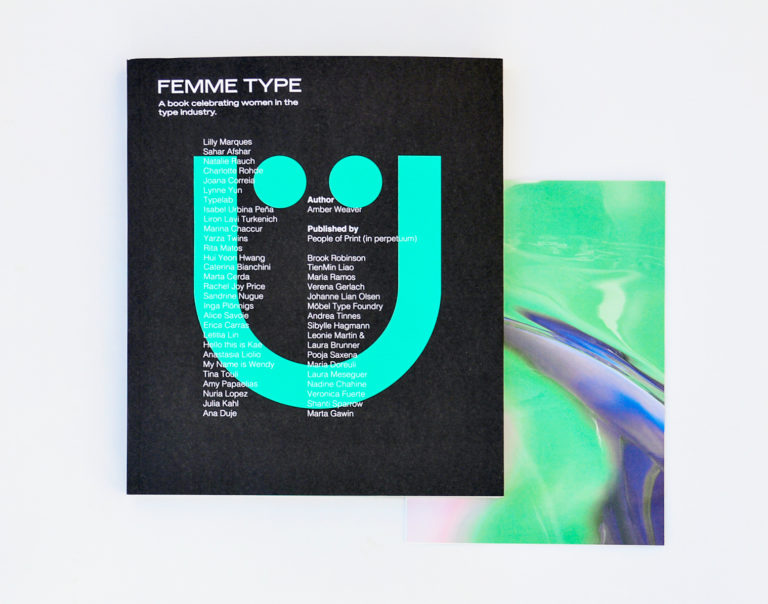
Mujeres en tipografía: Femme Type
«Estadísticamente hay más nombres de hombres que de mujeres en los libros de diseño. Tiene que haber más mujeres en el campo de la tipografía y la impresión que estén produciendo trabajos inspiradores, ¿por qué no son incluidas en estos libros y sus trabajos no aparecen en las plataformas online de inspiración?» Esta breve reflexión fue la que llevó a Amber Weaver a concebir Femme Type, una publicación exclusivamente femenina que «celebra» las obras de 40 mujeres de talento más que contrastado en la industria tipográfica con el objetivo de crear una obra que inspire a otras mujeres (y hombres) a seguir una carrera profesional en el campo de la Tipografía.
El concepto
Encontrar a estas mujeres y ensalzar sus trabajos en una publicación se convirtió en una misión para Weaver, lo que la llevó a crear una plataforma en Instagram con el fin de crear una comunidad y una red creativa donde compartir su pasión por las letras, además de llevar a cabo una campaña de Kickstarter, que en tan solo tres días consiguió la meta de financiación con un increíble apoyo por parte de multitud de patrocinadores anónimos. La respuesta de colaboración por parte de diseñadoras fue, también, más que positiva, ayudando a crear la simbólica y significativa obra que es Femme Type.
El libro
Femme Type se divide en tres secciones: ensayos, diseño tipográfico y tipografía.
Abre el libro el ensayo de la diseñadora de tipografía española María Ramos,sobre tipografía para máquinas de escribir y su influencia en las fuentes digitales, un profundo ejercicio de análisis sobre las tipografías monoespaciadas, en el que repasa las formas de los caracteres diseñados con unos propósitos concretos, el método de impresión y los factores que implican la apariencia final en papel, las novedades que trajeron los modelos de máquinas de escribir electrónicos y cómo, a pesar de que typewriter no es un estilo tipográfico concreto, se han diseñado tipografías que recrean la apariencia de textos escritos con estas máquinas. Como colofón, Ramos se detiene a analizar algunas de las más relevantes tipografías enmarcadas en esta tendencia desde el comienzo de la «era digital tipográfica» hasta nuestros días.
El segundo ensayo pertenece a TienMin Liao, diseñadora y tipógrafa neoyorquina especializada en lettering personalizado, tipografías para marcas y realización de logotipos kanji/chino. En su ensayo nos habla de la rotulación (o lettering) bilingüe, documentando alrededor de cincuenta ejercicios de combinación de sistemas de escritura latino y kanji, uno de los tres sistemas de escritura japonesa. En su texto, Liao examina las diferencias en el contorno, densidad y forma entre el latín y el kanji, hallando diferencias estructurales que suponen el principal reto a la hora de enfrentarse al desarrollo de un proyecto tipográfico bilingüe. Un extenso ensayo, lleno de detalles, que revela no solo una serie de enfoques para resolver el diseño bilingüe sino la riqueza de los sistemas de escrituras. No solo de latín vive la tipografía.
El apartado de diseño tipográfico muestra el espléndido trabajo de veintiocho talentosas diseñadoras de tipografía con breves reseñas biográficas y descripciones de los correspondientes proyectos, además de sus respectivas webs o contactos en las redes. Entre este elenco de altura, subrayamos, por el simple hecho de resultar de un modo u otro cercanas a quien suscribe, la presencia de Nuria López, Laura Meseguer, Joana Correia, Alice Savoie, Sandrine Nugue, Inma Plönnings, Nadine Chadine o Verena Gerlach. De todos modos, podemos decir que las veintiocho compañeras presentes en esta sección, algunas desconocidas hasta ahora, forman ya parte de nuestro acervo tipográfico.
Dentro de esta mismo sección figuran también tres artículos especiales firmados Typelab, Alphabettes y Slanted.
Este apartado muestra una calidad excepcional en conceptos, en ejecución, dibujo y usos, iluminando un carrusel de artes finales inspiradores y tremendamente comunicativos. Sistemas modulares, estructuras, deconstrucción, reinterpretaciones, diseños tipográficos inclusivos, experimentación, diferentes sistemas de escritura… un rico y pujante panorama creativo que ensancha los límites del diseño tipográfico.
El último apartado, llamado «Tipografía», incluye una entrevista con la fundadora de Hey Studio en Barcelona, Veronica Fuerte, y muestra los espectaculares trabajos de lettering y tipografía creativa de diseñadoras como Shanti Sparrow, Rita Matos, el estudio londinense Yarza Twins, My Name is Wendy o la barcelonesa Marta Cerdá. Una vez más descubrimos nombres que no teníamos en nuestro radar y volvemos a sentirnos abrumadas (y felices) por tanto talento y profesionalidad.
La guinda del pastel la pone Production Type con un espécimen de regalo incluido en la publicación.
Femme Type otorga visibilidad al trabajo de las diseñadoras, muestra un enriquecedor escenario en el campo tipográfico y es, sin duda, una obra inspiradora para diseñadoras y diseñadores del presente así como una herramienta educativa para las siguientes generaciones.
Ficha técnica
• Título: Femme type | A book celebrating women in the type industry
• Autora y diseñadora: Amber Weaver
• Editorial: People of print
• Género: tipografía
• Idioma: inglés
• Encuadernación: tapa blanda
• Tintas: cmyk + Pantone 3245U
• Papel: Fedrigoni Arcoprint. Cubierta 300 g, interior 100 g
• Medidas: 250 x 210mm
• Páginas: 272
• Tipografías: Mars Extended y Condensed de Production Type y Suisse Int’l Mono Regular de Swiss Typefaces